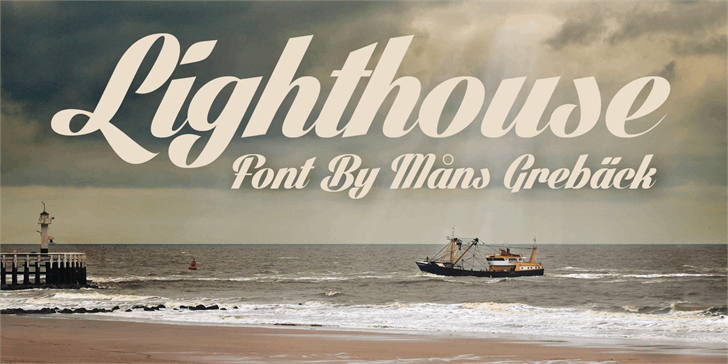
A Lighthouse é uma elegante fonte script criada por Hamilton que se destaca por seu charme e beleza natural. Este estilo delicado tem sido apreciado por designers que procuram um recurso gráfico fluido para projetos de marketing, editorial ou identidade corporativa. Com traços finos e movimentos suaves, a Lighthouse oferece uma abordagem versátil para diferentes aplicativos visuais. Seu charme não só se destaca em peças editoriais comuns como logotipos e nomes de produtos, mas também se torna um elemento fascinante em designs digitais, permitindo que designers criem visualizações únicas. Navegar na web para o site do designer pode levar você a uma variedade de outras fontes interessantes. Combinar esta elegância com outros estilos, Lighthouse tem algo especial e único para oferecer aos artistas digitais em busca de um recurso gráfico refinado e autêntico. Não perca tempo pesquisando; visite o site do designer para adquirir sua própria licença comercial da fonte Lighthouse hoje.